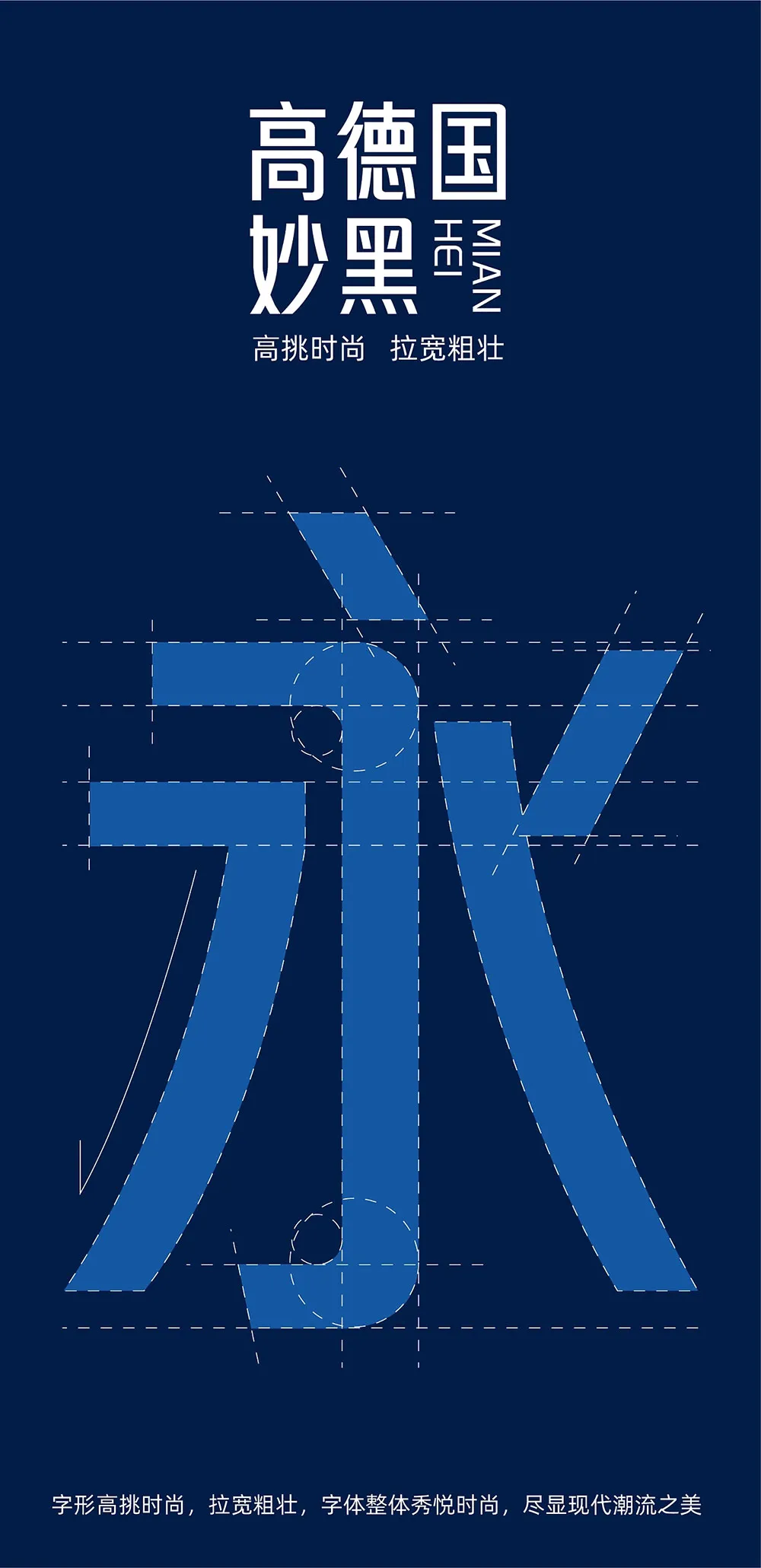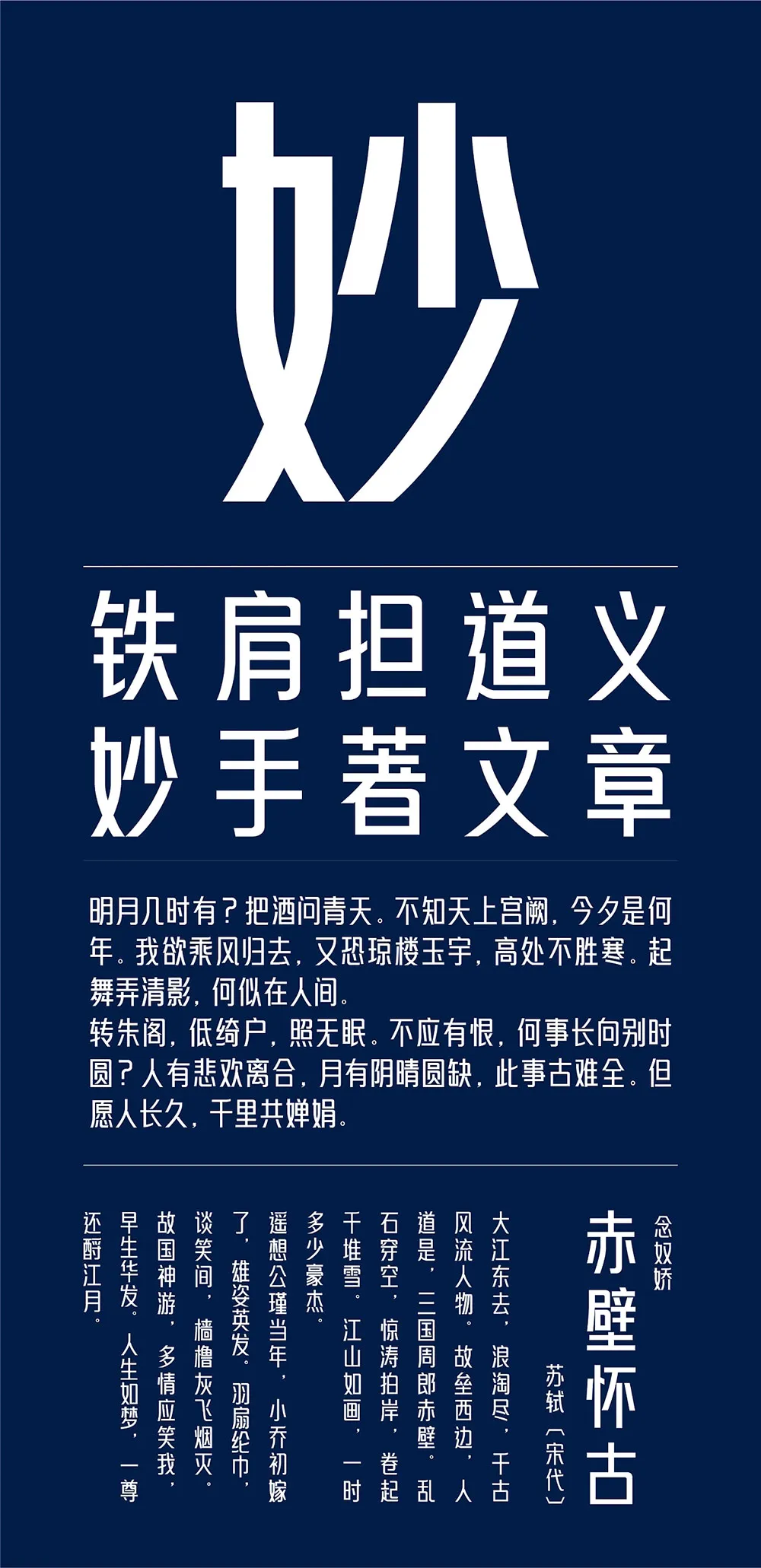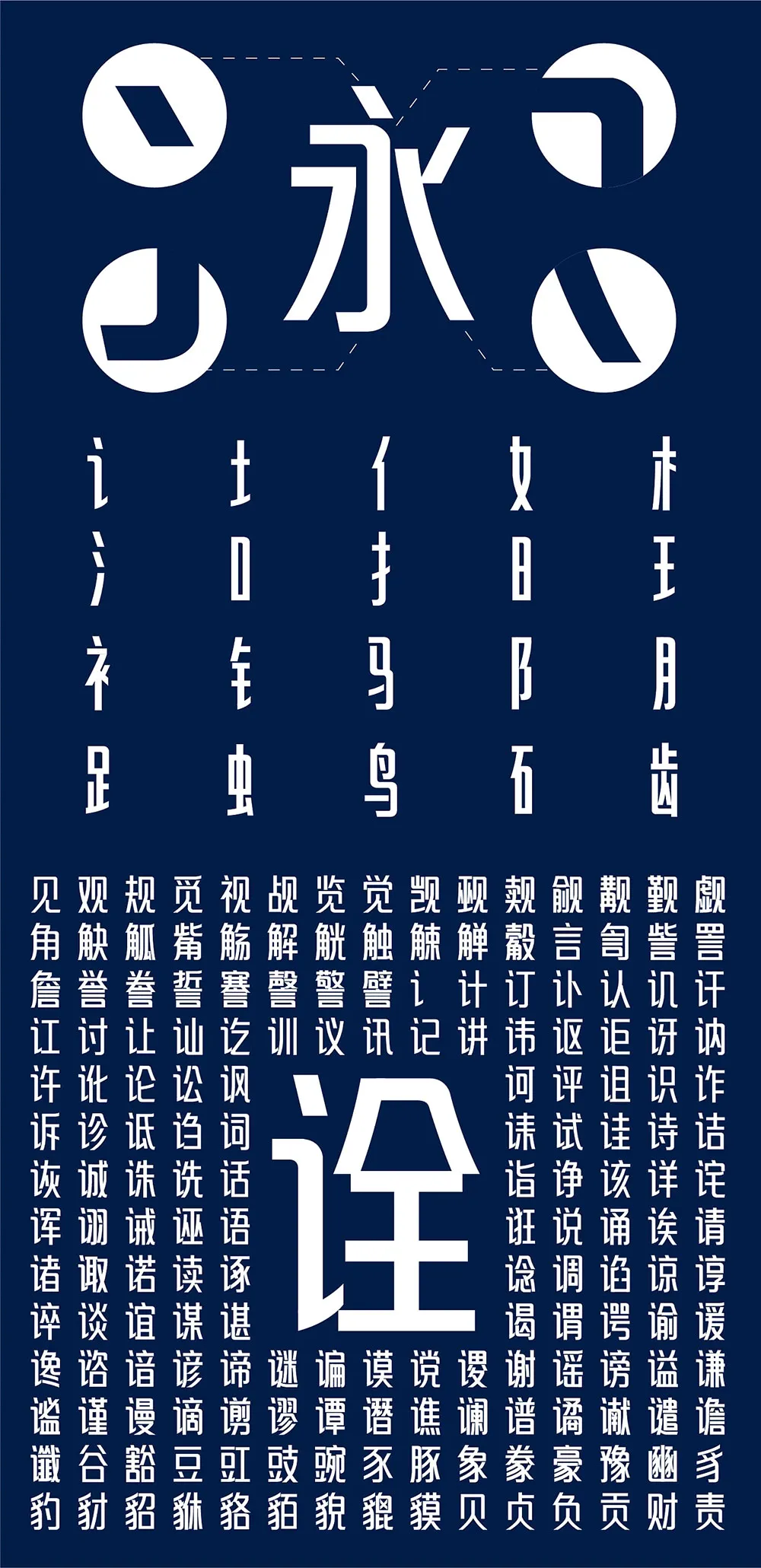
寫在前面:字體一直是我的摯愛,從小就學習毛筆字,總是喜歡寫寫畫畫,把好的字體都儲存在審美的基因裡,見到好的字體就如獲至寶。其實愛好才是每個人最好的工作動力,因為在以後從事品牌設計中總會遇到字體設計,好多機械性的字庫字體顯然解決不了設計人的多樣性、個性化需求,為了解決品牌獨特的一面,就會設計無數個性品牌字體,慢慢地字體就成了離不開的夥伴。為解決品牌設計麻煩,何不為品牌設計人提供獨特、個性類似商家定製字體?這樣既解決了設計人的麻煩,也為企業商戶提供了多樣性選擇。
倉跡高德國妙黑體:這是一款收藏幾年前的參賽樣稿,從動筆到完工,陸續也有一年有餘,總算能和大家見面了。當初這款字體有和字體廠商談過,不過價格太低,我放棄合作,打算自己開發這款時尚感十足的字體,開發的時候其實幾經修改,因為黑體款式比較多,稍微不注意就有撞車危險,感覺修改就是避坑,不管如何今天和大家見面了。
妙黑體高挑時尚,拉寬粗壯,做品牌設計必備,做廣告標題良藥,獨特的高挑結構,使字體在商業創意設計中,可以更好的將字形與創意互相結合應用,能更好的為設計師服務,字體在各種行業眾多場景都有出彩表現。
倉跡高德國妙黑,字庫字數:7155字,字體風格:時尚、潮流型,適用範圍:品牌標誌、招牌、包裝、海報、影視綜藝、廣告、遊戲、漫畫等。